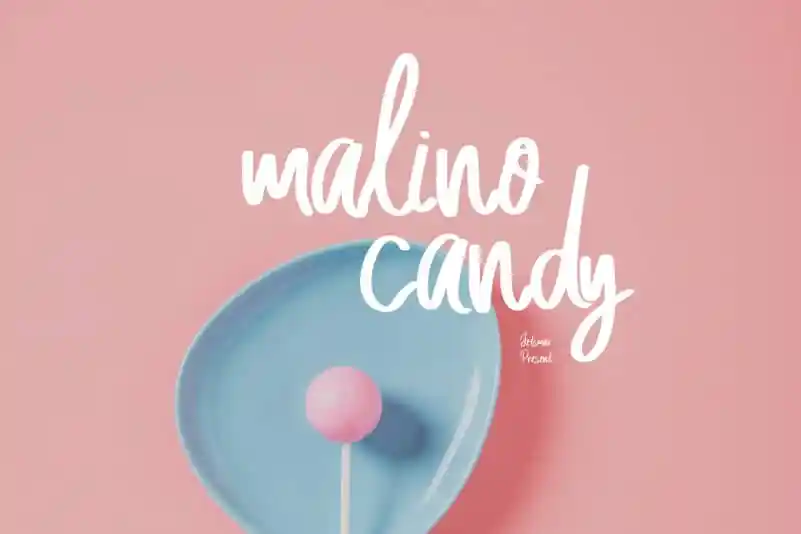
Malino Candy Script Font – Download Grátis
A Malino Candy Script Font é uma elegante fonte escrita à mão que transmite alegria e delicadeza. Suas curvas suaves e encantadoras dão vida a um tema delicioso, criando um contraste divertido entre seu lado simples e carinhoso. Esta fonte traz um toque de magia aos projetos gráficos, fazendo-os se destacarem ainda mais com suas formas fluidas e sutis. Seja em logotipos, selos ou designs para crianças, a Malino Candy Script Font é perfeita para aqueles que buscam uma fonte criativa para seus trabalhos gráficos. Combinar sua delicadeza com os elementos coloridos do mundo dos doces pode tornar qualquer projeto um verdadeiro sucesso.